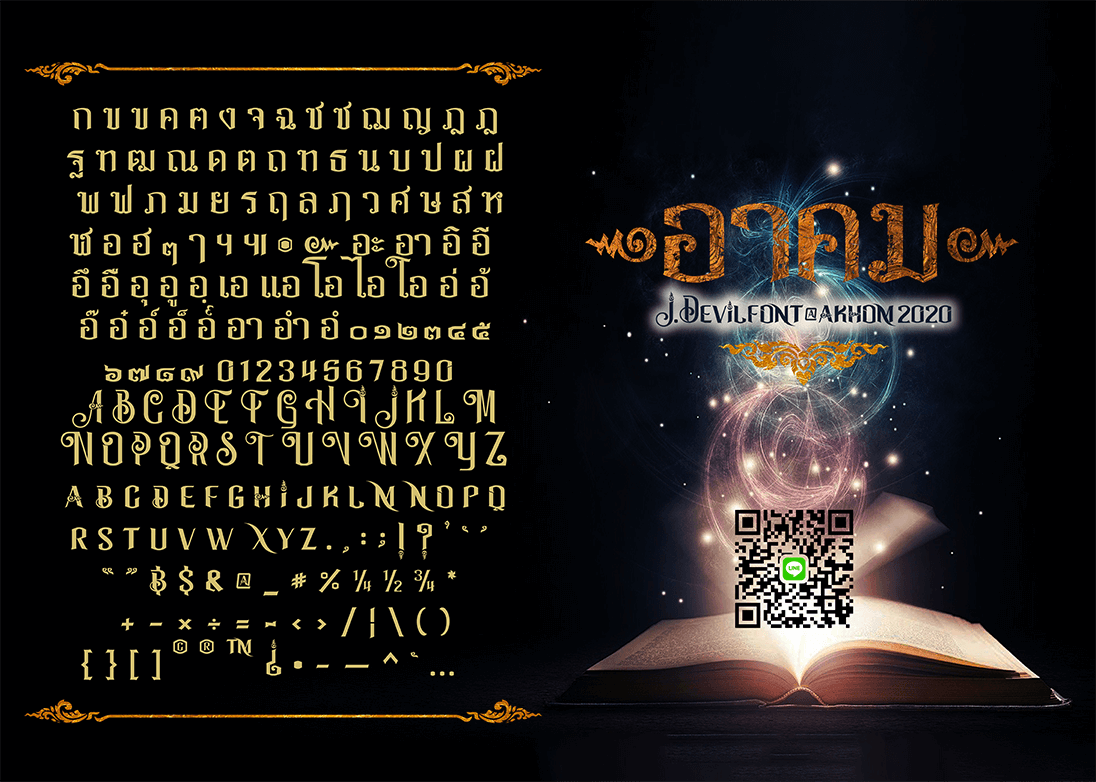
อาคม2020 (j.devilfont@akhom2020)
หลังจากที่เพื่อนๆ สมาชิกในกลุ่ม ฟอนต์กูรู  #กลุ่มsk #งานสกรีน #งานป้าย เพื่อนๆ ฟรีแลนซ์ที่ช่วยเป็นกำลังใจกับผลงาน ฟอนต์จุติ2020 v.2 ผมกันไปบ้างแล้ว ปัจจุบันผมได้เปิดตัวฟอนต์ตัวที่ 2 ชื่อ อาคม2020 แนวอาลักษณ์กันบ้าง
โดยฟอนต์ตัวนี้มี 5 file ตามรายละเอียดที่แนบด้านล่าง # อักษรภาษาไทยเพิ่มลูกเล่นในการเปลี่ยนหางตัวอักษร ช ซ ศ ส ฬ ฮ  ได้เองเมื่อพิมพ์วรรณยุกต์ + ใช้ mark เข้ามาจัดวรรณยุกต์ +  ( ลูกเล่นที่ โ ใ ไ ที่ยืด-หด / เจาะร่องให้กับ โ ใ ไ ความสูงได้เองเมื่อตำแหน่งวรรณยุกต์ชนกับ โ ใ ไ ) + จัดช่องไฟชดเชยความห่างระหว่างตัวอักษร
หนึ่งในลูกเล่นของฟอนต์อาคม – ตัวอักษรที่มีหาง เวลาเจอวรรณยุกต์ตัวอักษรจะเปลี่ยนหางได้ครับ
และอีกหนึ่งลูกเล่นของฟอนต์อาคม – เวลา พิมพ์วรรณยุกต์ชั้น 2 ปกติจะทับกับ ใ โ เจาะมันดิครับ จะได้ทำให้อ่านง่ายๆ สบายตาครับ
อีกลูกเล่นของฟอนต์อาคม – เวลาพิมพ์วรรณยุกต์ชั้น 2 ปกติจะทับกับ ใ โ ยกสูงลอยได้ครับ จะได้ทำให้อ่านง่ายๆ สบายตาครับ
มาชมตัวอักษรภาษาอังกฤษใน ฟอนต์อาคมกันบ้างครับ กว่าจะจัดเรียงช่องไฟได้ลงตัวกินเวลานานมากกว่าจะลงตัว ลูกเล่นในตัวอักษร Eng ตัวพิมพ์ใหญ่จะมีการเกี่ยวหาง บลาๆๆๆๆๆ
1. j.devilfont@Akhom2020-Normal ( ธรรมดาไว้ปรับแต่งได้ )
ตัวอักษรมีหาง ช ซ ศ ส ฬ ฮ เปลี่ยนหางได้เวลาพิมพ์วรรณยุกต์ชั้น 1
+ ลูกเล่น ( ไ โ ใ ) ยืดขึ้น-ลง เวลาเจอวรรณยุกต์ชั้น 2
2. j.devilfont@Akhom2020-Regular ( ปกติ )
ตัวอักษรมีหาง ช ซ ศ ส ฬ ฮ เปลี่ยนหางได้เวลาพิมพ์วรรณยุกต์ชั้น 1
+ ลูกเล่น ( โ ใ ) เจาะเว้นร่อง เวลาเจอวรรณยุกต์ชั้น 2 + ปรับแต่งช่องไฟ
3. j.devilfont@Akhom2020-Italic ( ตัวเอียง )
ตัวอักษรมีหาง ช ซ ศ ส ฬ ฮ เปลี่ยนหางได้เวลาพิมพ์วรรณยุกต์ชั้น 1
+ ลูกเล่น ( โ ใ ) เจาะเว้นร่อง เวลาเจอวรรณยุกต์ชั้น 2 + ปรับแต่งช่องไฟ
4. j.devilfont@Akhom2020-Texture  ( ตัวแตกๆ เหมือนใบปะหน้าฟอนต์อาคม )
ตัวอักษรมีหาง ช ซ ศ ส ฬ ฮ เปลี่ยนหางได้เวลาพิมพ์วรรณยุกต์ชั้น 1
+ ลูกเล่น ( โ ใ ) เจาะเว้นร่อง เวลาเจอวรรณยุกต์ชั้น 2 + ปรับแต่งช่องไฟ
5. j.devilfont@Akhom2020-3D  ( 3D )
ตัวอักษรมีหาง ช ซ ศ ส ฬ ฮ เปลี่ยนหางได้เวลาพิมพ์วรรณยุกต์ชั้น 1
+ ลูกเล่น ( ใ ) เจาะเว้นร่อง เวลาเจอวรรณยุกต์ชั้น 2 + ปรับแต่งช่องไฟ